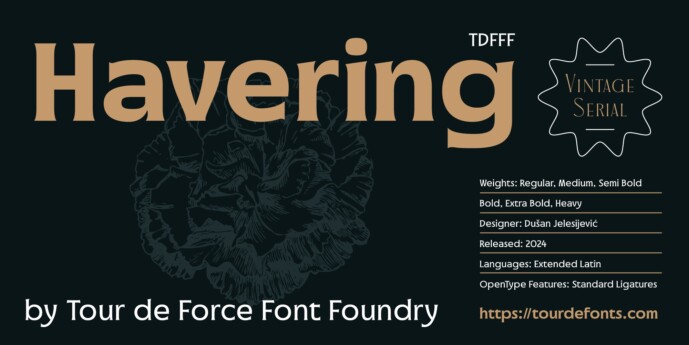
Havering Font Family
Designer: Tour De Force
À propos de la famille Havering Police
Havering est une nouvelle addition aux familles Vintage Serial police .
Disponible en 6 graisses, Havering est une famille de caractères police avec des empattements doux à la manière vintage. Contrairement à la proportion de lettres la plus courante dans polices, Havering contient des lettres larges, condensées et de largeur normale. Cela a été fait dans le but d’obtenir une plus grande dynamique visuelle dans les mots.
Ce style de police a une large gamme d’utilisation, des logos, branding, conception d’emballage, signalisation aux sites Web, applications et ebooks.
Havering contient des Ligatures standard en tant que caractéristiques OpenType.